Kyrillische Schrift
Im 9. Jahrhundert schufen die bulgarischen Mönche Kyrill und Method eine Schrift, die den slawischen Sprachen ein eigenes Gewand gab. Heute ist sie in Russland, Bulgarien, Serbien und vielen weiteren Staaten Osteuropas in Gebrauch.
Eine Schrift für die Slawen
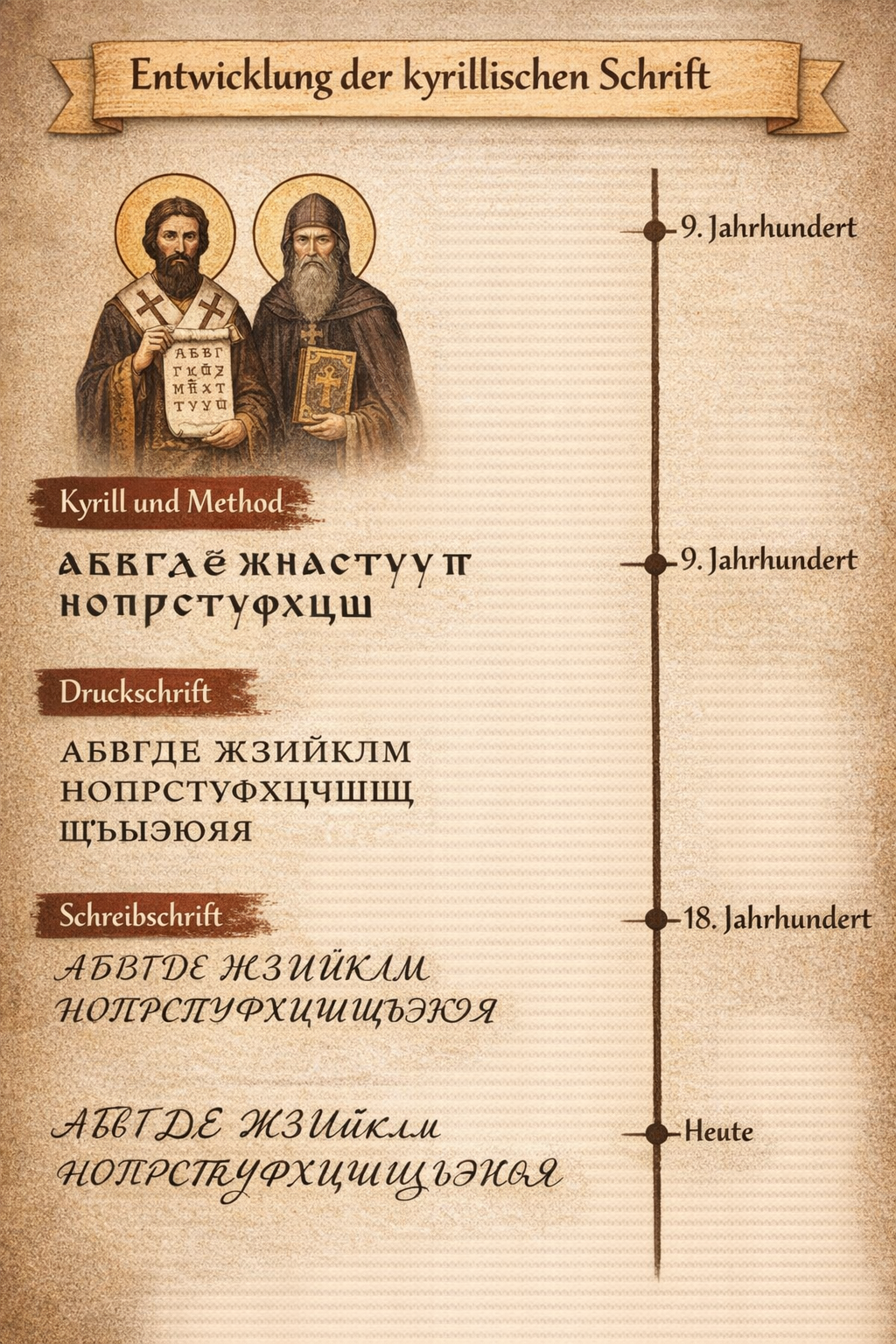
9. Jahrhundert
Kyrill und Method
Aus der älteren glagolitischen Schrift entwickelt, übernimmt das kyrillische Alphabet Buchstabenformen aus dem Griechischen und ergänzt sie um Zeichen für die spezifischen slawischen Laute. Mit der Bibelübersetzung wird es Träger einer ganzen Kulturregion.